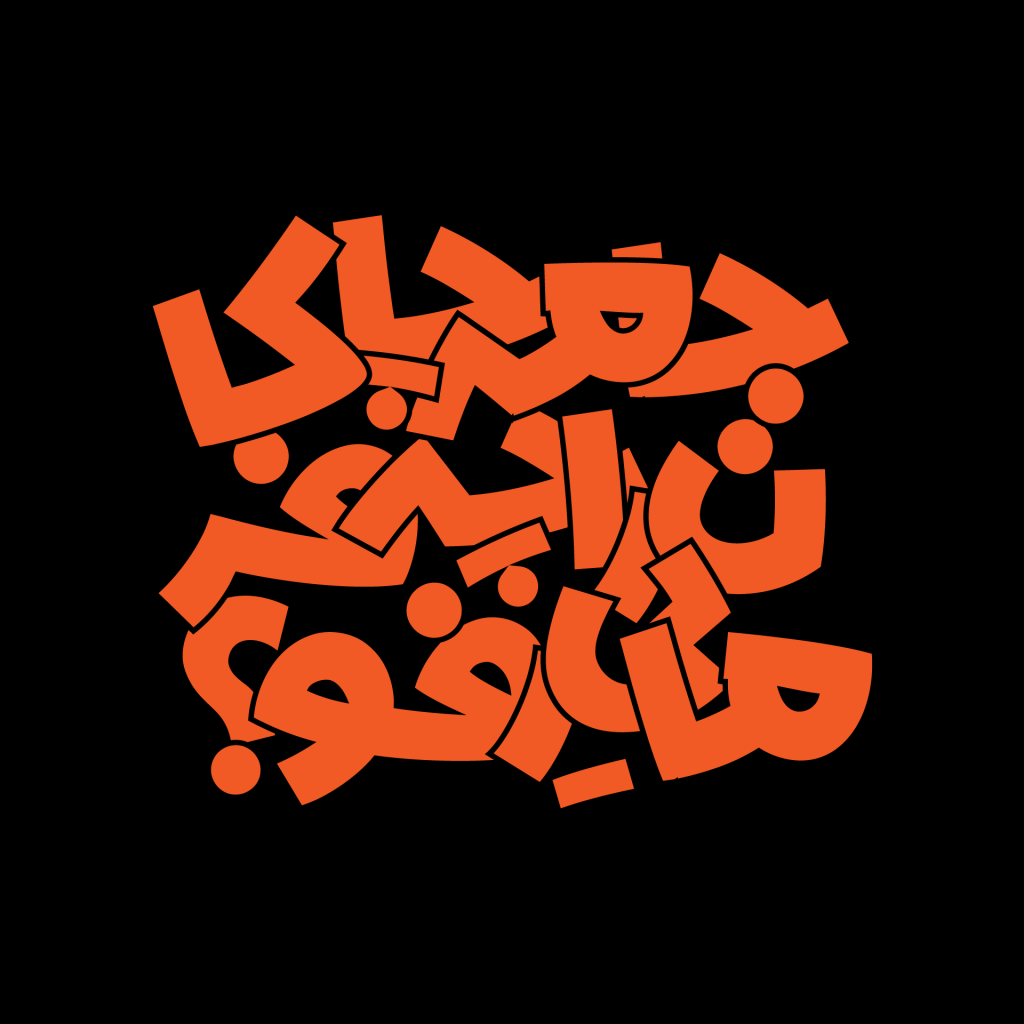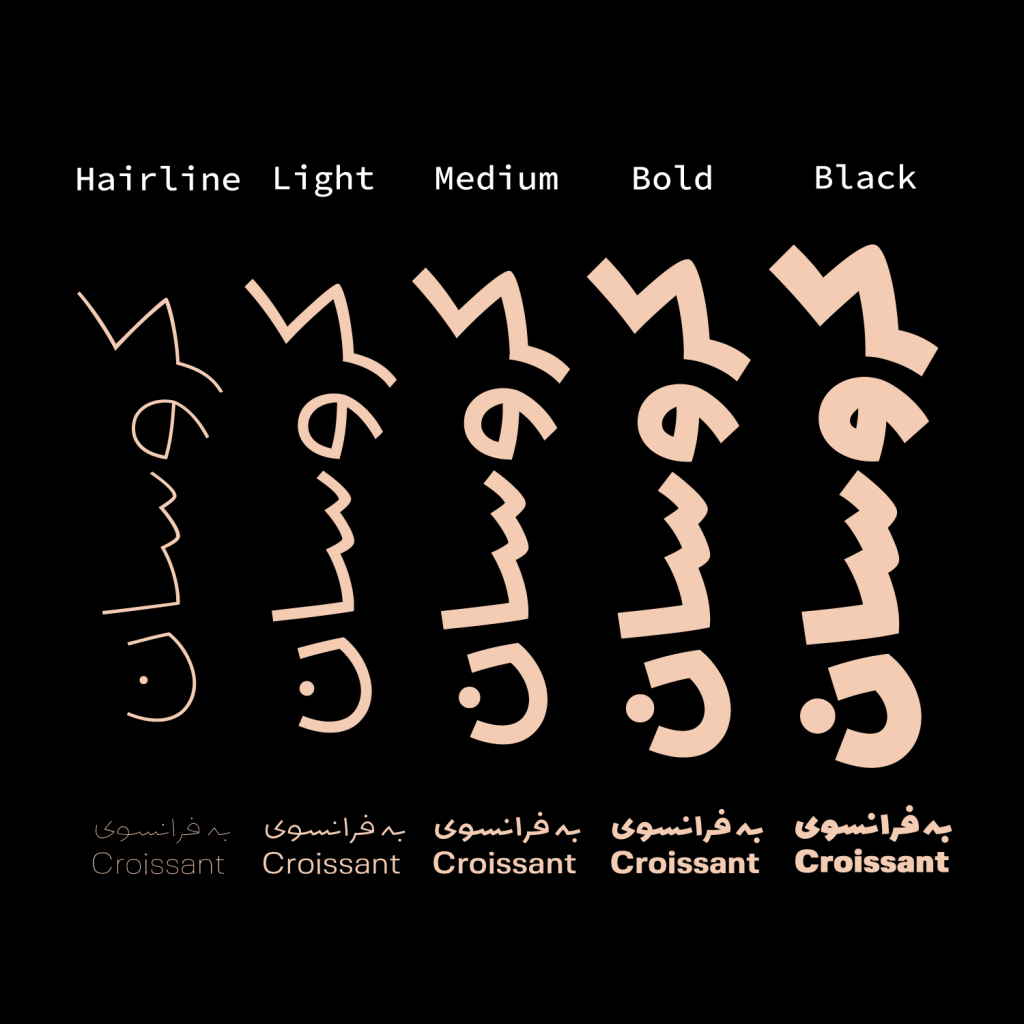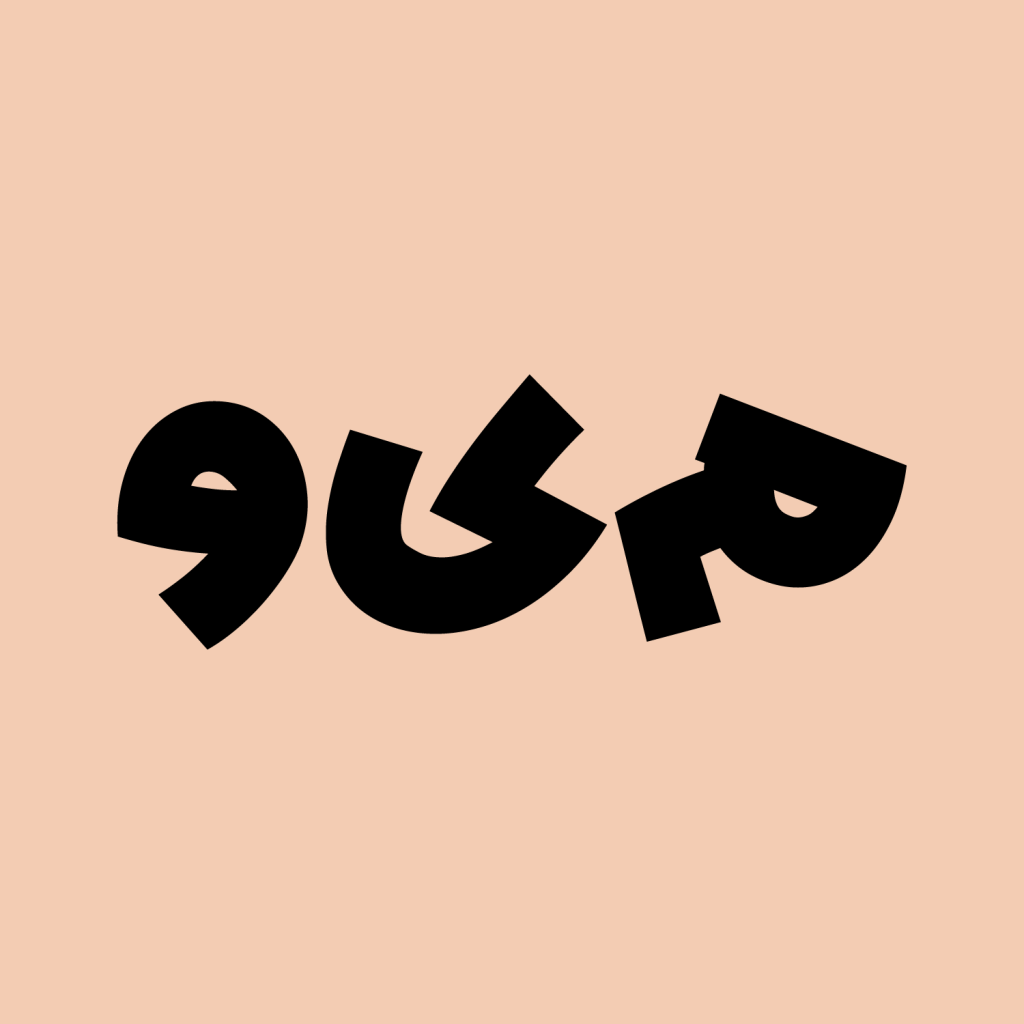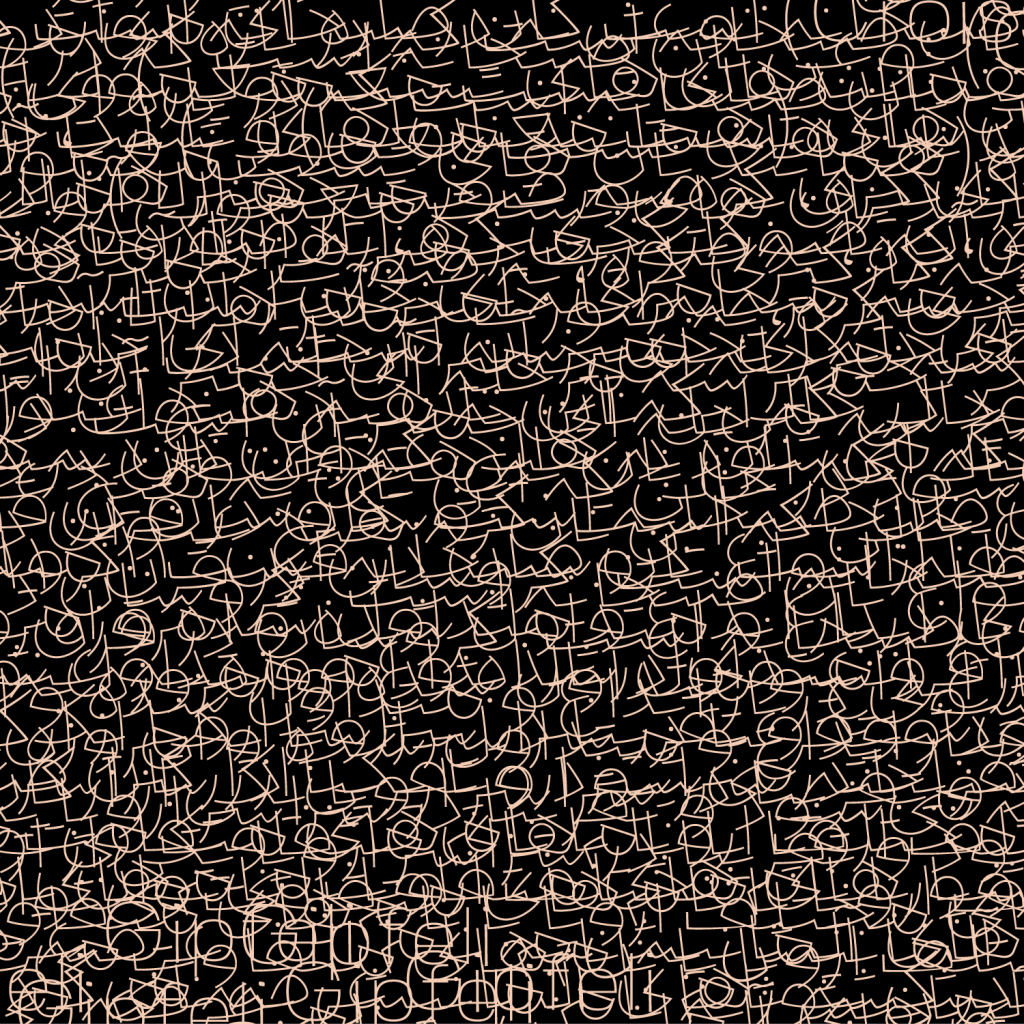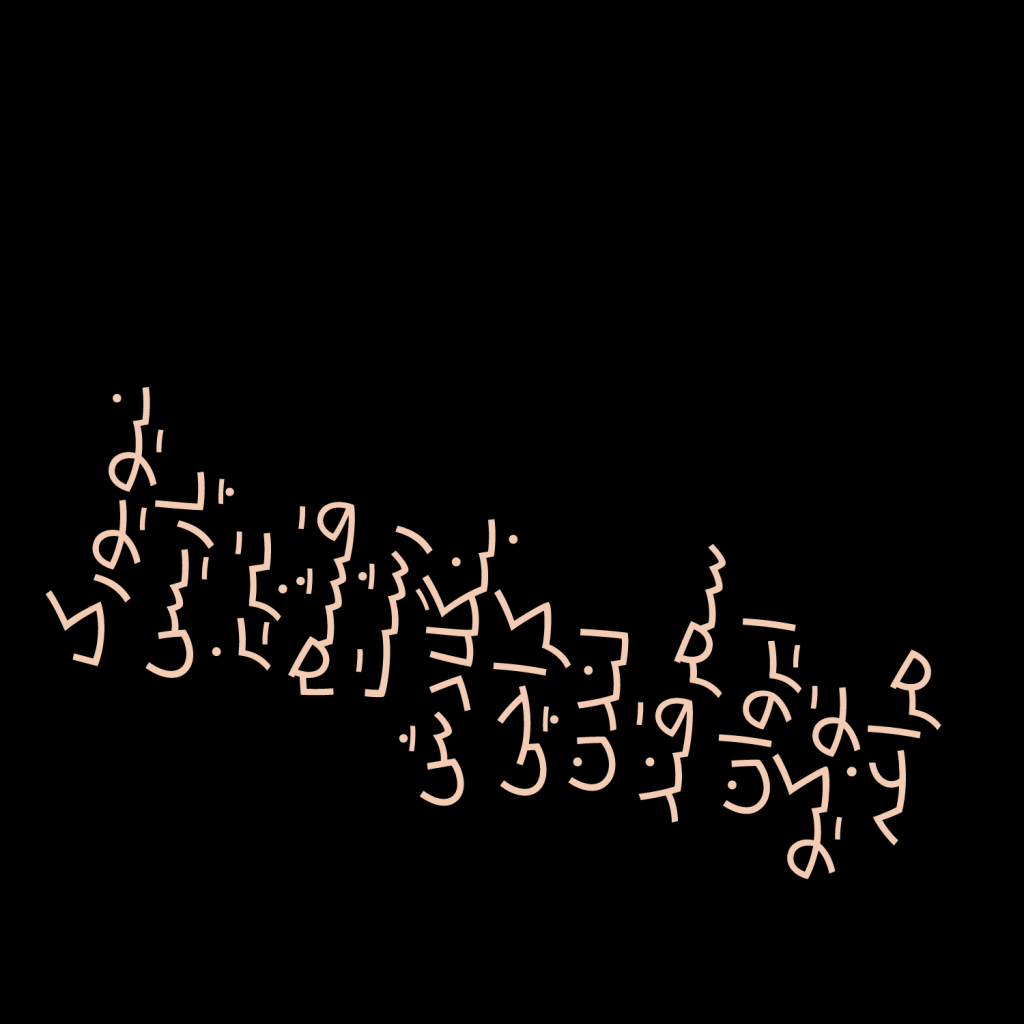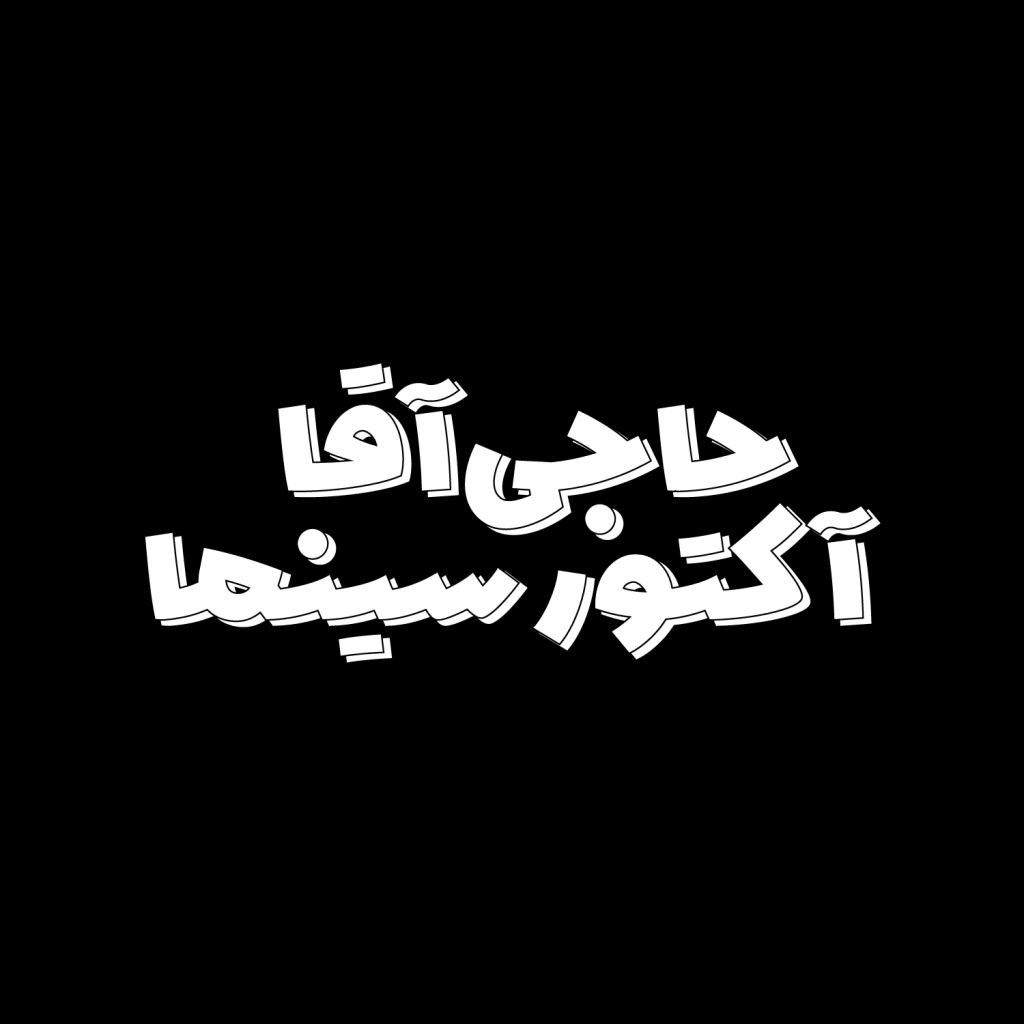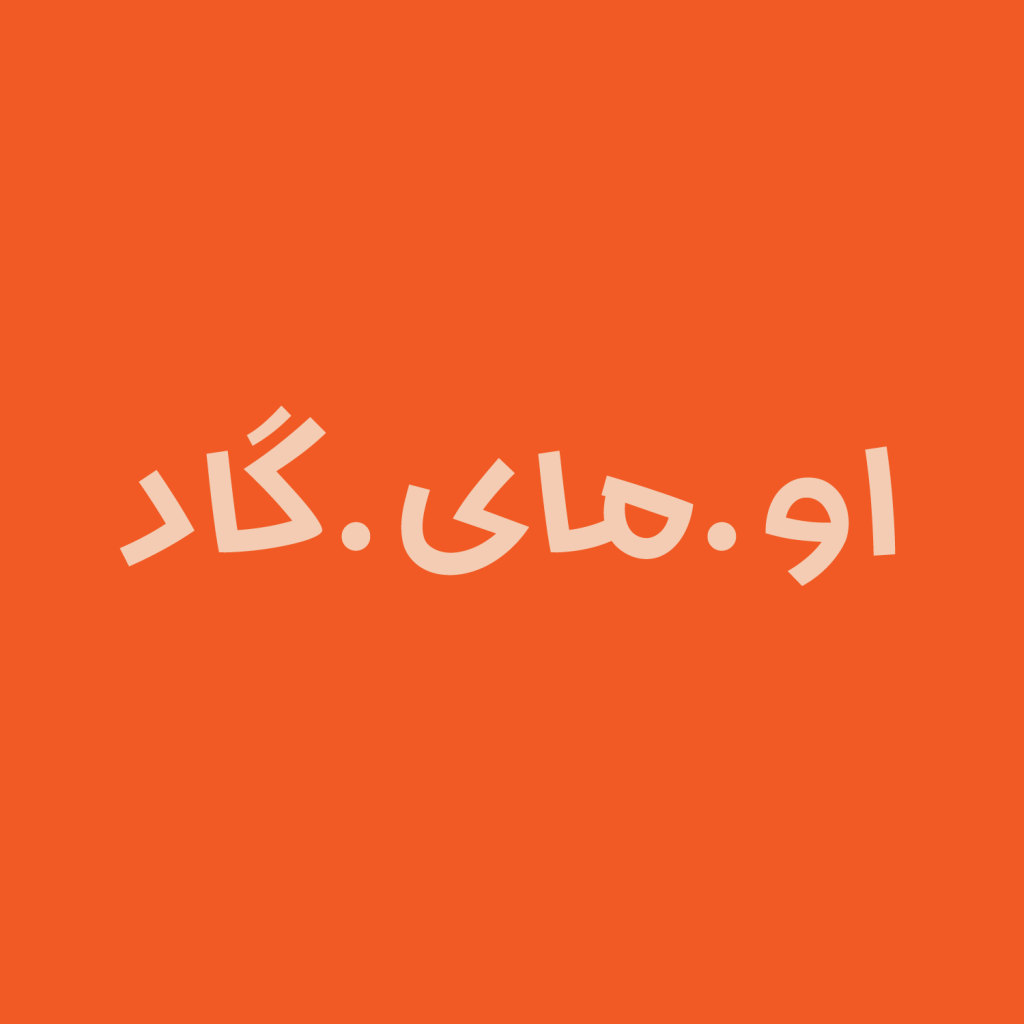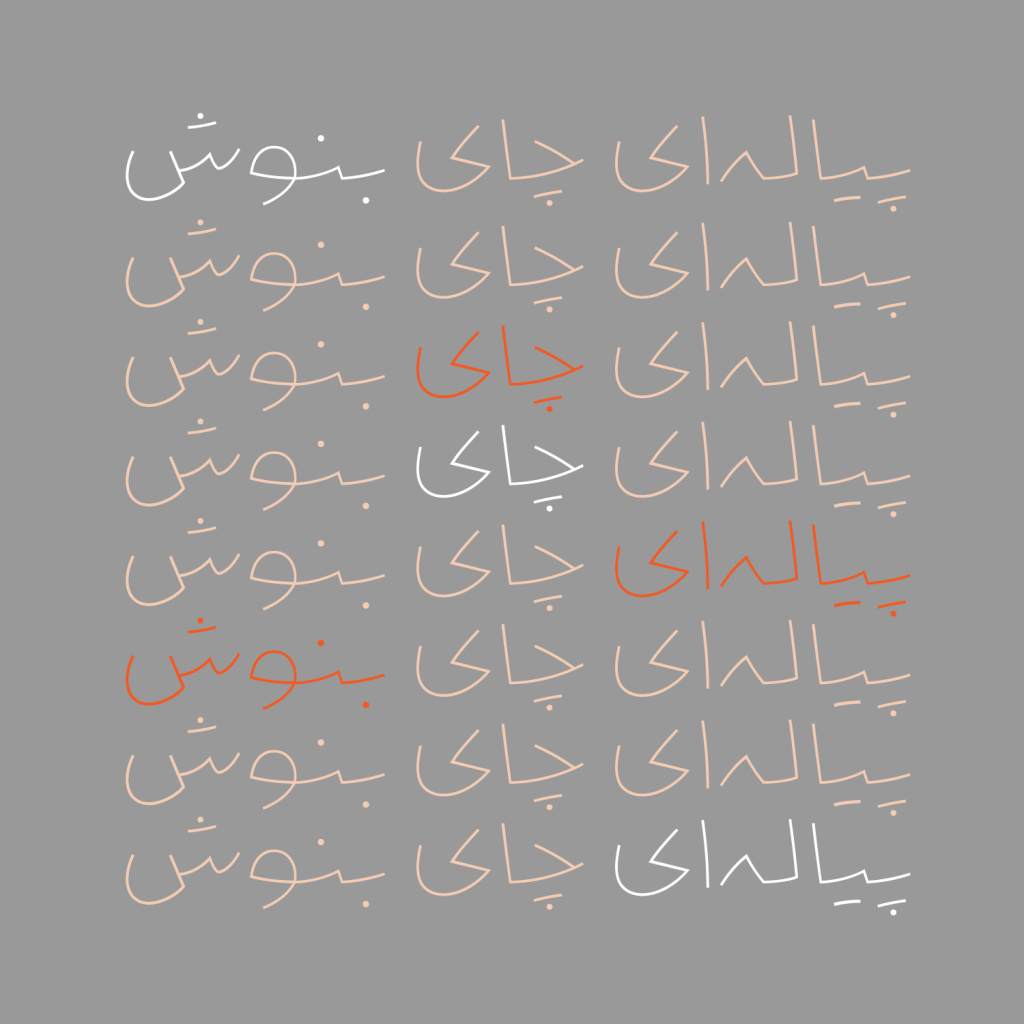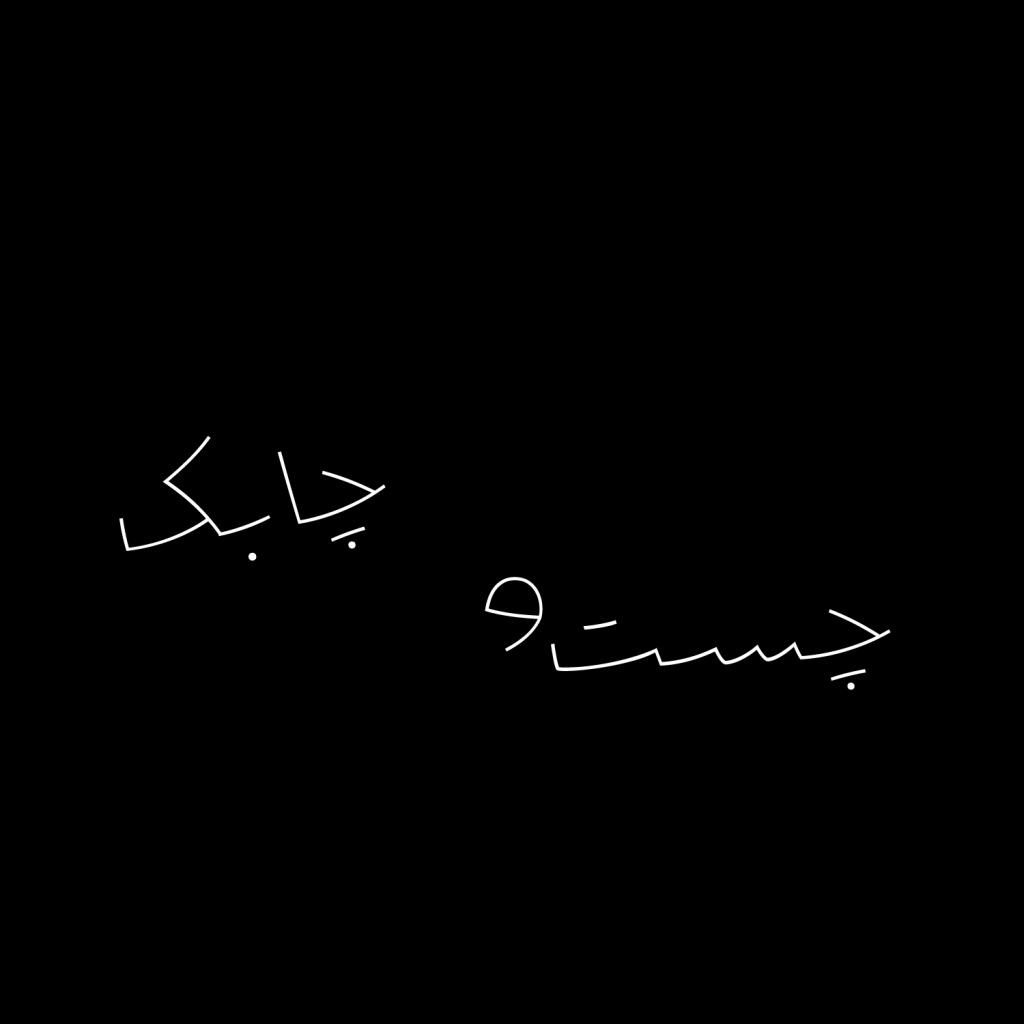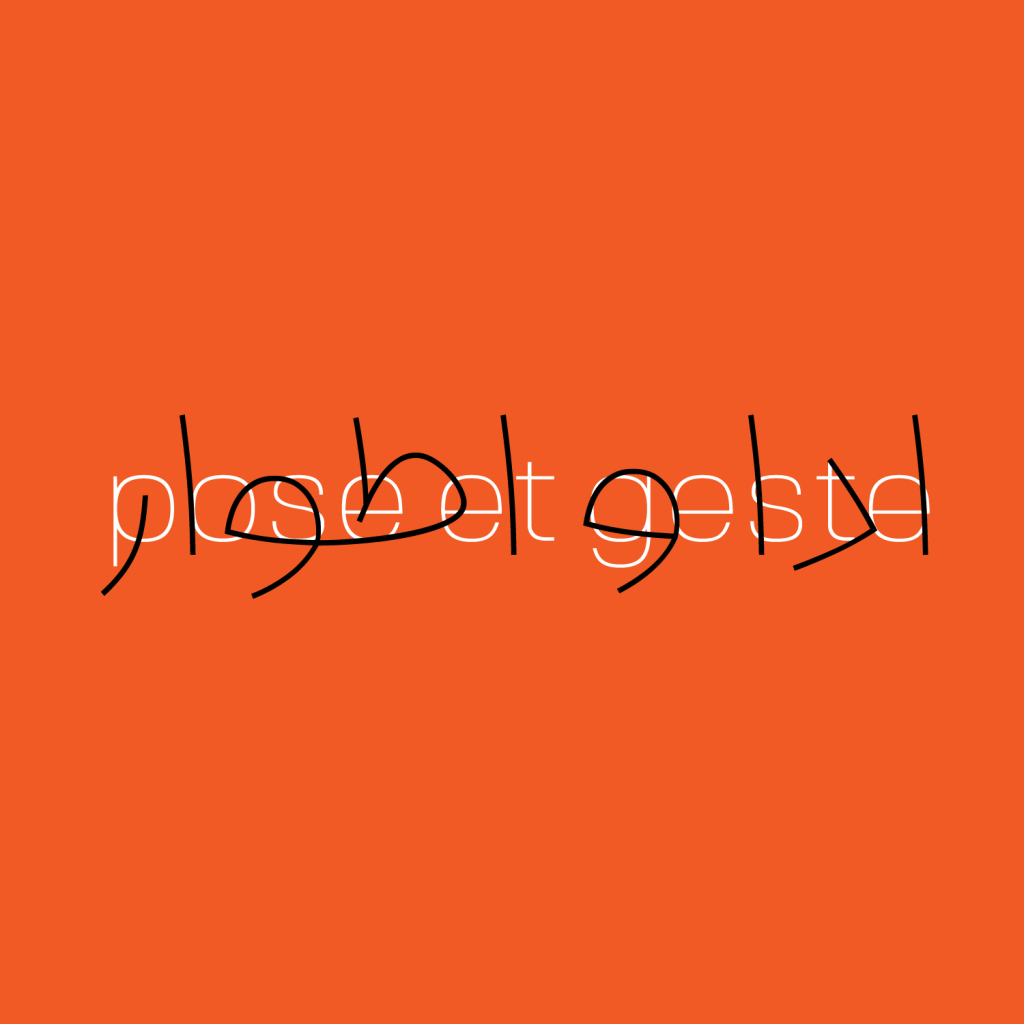
فونت کروسان قلمی جدید امروزی نو پویا و بانشاط است مناسب برای تیتر های تبلیغاتی و محاوره ای برای عناوین و متون کوتاه می باشد . با ما همراه باشید و از دیدن چنین تایپ فیس زیبایی لذت ببرید.
فونت کروسان -قلمی خاص و ویژه برای شما
فونت کروسان قلمی روان و پویاست .این تایپ فیس توسط طراح محترم آقای علی پزشک در اولین نسخه با 5 وزن مختلف طراحی و ایجاد گشته است. فرم های طراحی حروف و گلیف های این تایپ فیس نرم و روان و متعادل است اما از استخوان بندی و شاکله فونت فارسی پیروی و تبعیت می کند. از خانواده هندسی است.
پشتیبانی از 5 وزن ( از قطر مو تا وزن سنگین Black)
در این تایپ فیس تقابل سنت با مدرنیته به طرز زیبایی هماهنگ و هم صدا شده است . اولین نسخه از این قلم برای زبان فارسی در ۵ وزن آماده شده است. هر وزن از این فونت در عین تعلق به یک خانواده، شخصیت جداگانه داشته و از دیگر وزن‌ها قابل تشخیص است. این تایپ فیس زیبا از ضخامتی نازک به اندازه قطر مو یا HairLine شروع تا ضخامت آن به Black می رسد. پس این قلم دارای تنوع وزنی کاملی برای شما می باشد.
• Hairline: مناسب برای نوشته های بسیار ریز و ظریف..
• Light: متون‌ کوتاه و نوشته های کوچک.
• Medium: وزن تعادلی برای استفاده‌های عمومی در متون بلند.
• Bold: جهت تیتر ها و عناوین بولد و نمایشی.
• Black: با ضخامتی مثال زدنی و جسور در عناوین و تیتر های تبلیغاتی برای پوسترها و …..
کروسان مناسب برای پوستر و حتی لوگو تایپ
کروسان ساخته و پرداخته شده برای جذب نگاه مخاطبان چرا که دارای ویژگی و شخصیت نمایشی و جذاب است و به دنبال تسخیر نگاه مخاطبان به پیکر وجودی خود می باشد. این قلم از نقطه نظر فرم طراحی گلیف ها و حروف و هم خانواده گی شبیه به فونت والهالا می باشد. که شما عزیزان می توانید از طریق لینک داخلی از آن دیدن فرمائید.
این تایپ فیس به روز و مدرن و در عین حال زیبا مناسب برای فضای تبلیغاتی و تیتر های جذاب می باشد. کروسان برای استفاده در فضای شهری، فضای دیجیتال، عنوان و متن‌های كوتاه، پوستر و و حتی لوگوتایپ مناسب است
پشتیبانی از اعداد فارسی و زبان های دیگر
این قلم با دارا بودن اعداد فارسی و پشتیبانی از آنها و همچنین دارا بودن اعراب مختلف و لیگچرهای و حروف عربی را هم در دل خود دارد و از زبان عربی هم پشتیبانی میکند .در تصاویر زیر نمونه هایی از نوشتار با این فونت به نمایش گذاشته شده است شما دوستان عزیز می توانید از این فونت جذاب و پویا دیدن کرده و آن را دانلود کنید.